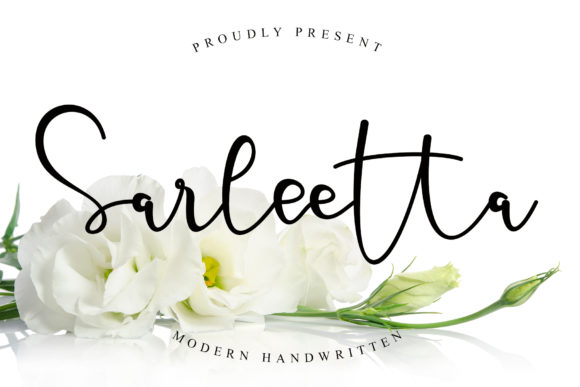
Creativefabrica Sarleetta Font
[Creativefabrica] Sarleetta Font
Сарлетта - сладкий и скорописный рукописный шрифт.
Этот нежный шрифт будет великолепно смотреться на разнообразных дизайнерских идеях.
Он добавит радостный и романтичный штрих в каждый из ваших проектов!